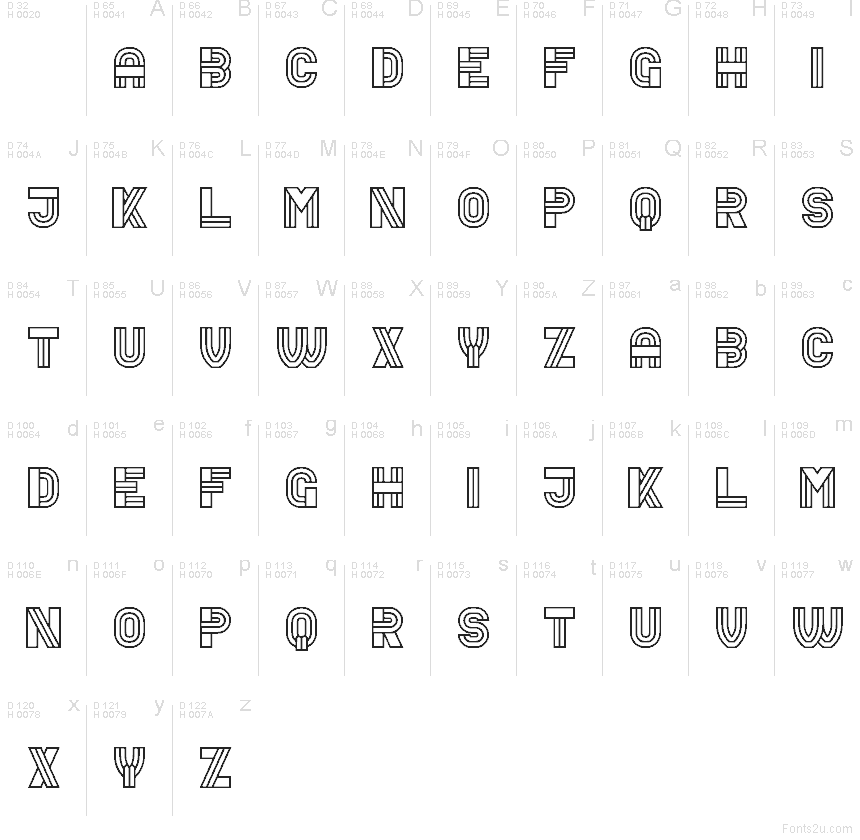
Hertz Extravagant od Vladimira Nikolice je bezplatné dekorativní display písmo s geometrickou konstrukcí tvořenou pruhy. Jeho písmena využívají paralelní úsečky, hranaté rohy a otevřené vnitřní prostory, což celému setu dodává výrazný konturovaný rytmus.
Hertz Extravagant se skvěle hodí pro titulky na plakátech, grafiku alb, logotypy, letáky na akce a krátké nápisy, kde opakující se vzor linek sám o sobě vytváří vizuální efekt. Tento bezplatný font se hodí také na etikety obalů a redakční prvky, které vyžadují grafický, strukturovaný vzhled namísto běžného písma pro hlavní text.